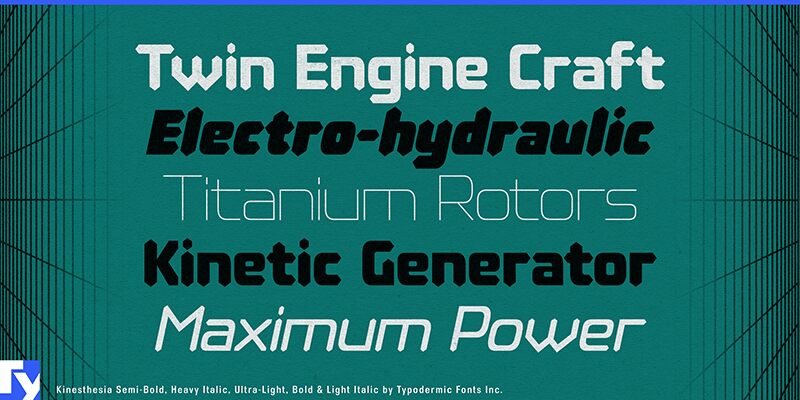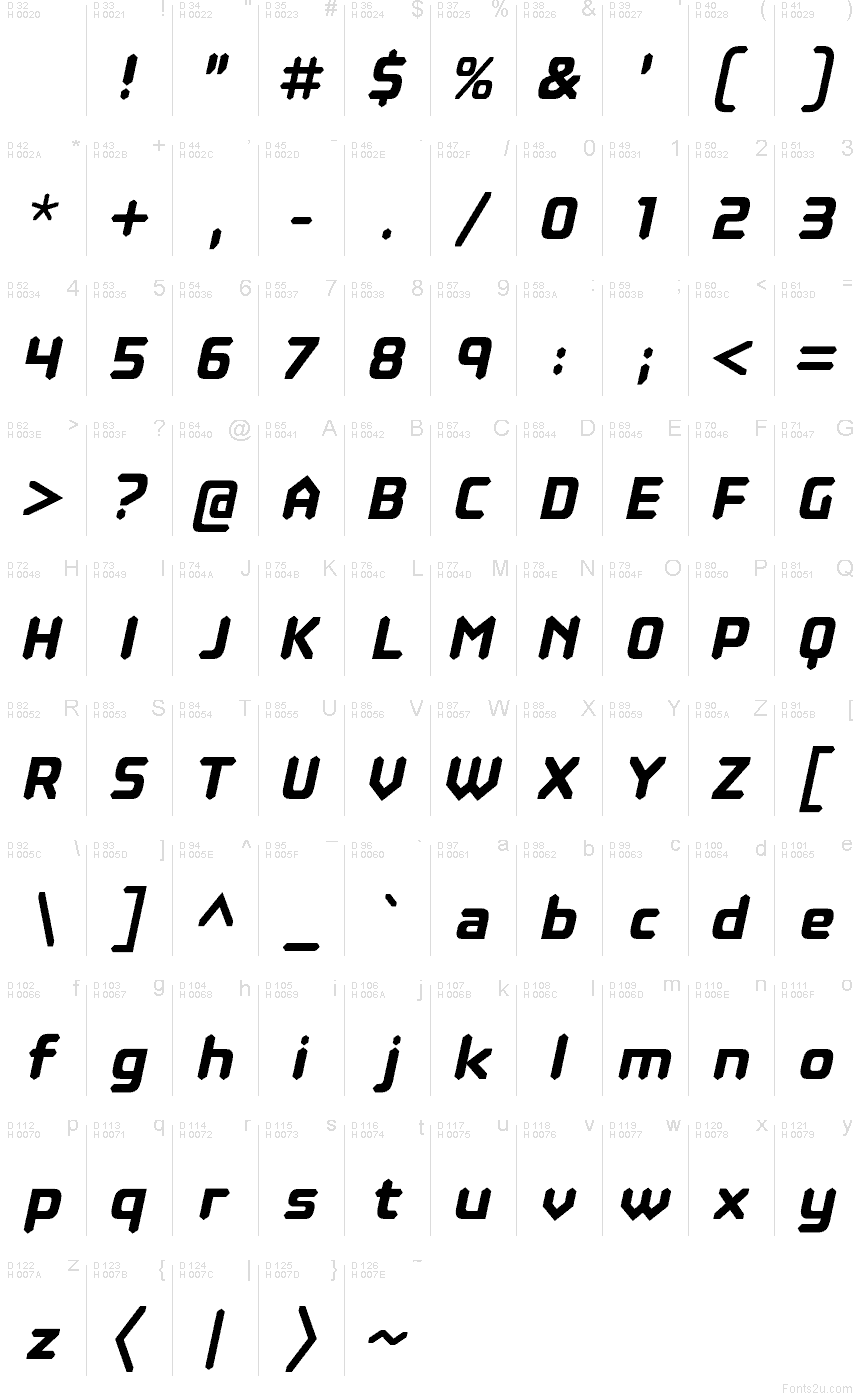
Kinesthesia od Typodermic Fonts Inc. je bezplatné techno titulkové písmo s rýchlym, šikmým rytmom a kompaktným, aerodynamickým výrazom. Písmená kombinujú ostré rezy so zaoblenými obdĺžnikovými krivkami, vďaka čomu pôsobí písmo strojovo aj športovo, s jemným nádychom ranej digitálnej estetiky namiesto chladného sci-fi dojmu.
Prirodzene zapadne do hernej grafiky, brandingu aplikácií, hudobných vizuálov, plagátov a titulkov, kde potrebujete bezplatné písmo, ktoré dodá pohyb bez zbytočného vizuálneho šumu. Vďaka kurzívnemu sklonu a ostrým spojom výborne funguje pri krátkych názvoch produktov, titulných stránkach a v dizajne rozhraní, najmä ak chcete, aby text pôsobil svižne a technicky precízne.
Kinesthesia SemiBold Italic od Typodermic Fonts je bezplatné techno titulkové písmo.
Kinesthesia nahrádza bežné ploché alebo zaoblené ukončenia ťahov zrezanými koncami v tvare diamantu.